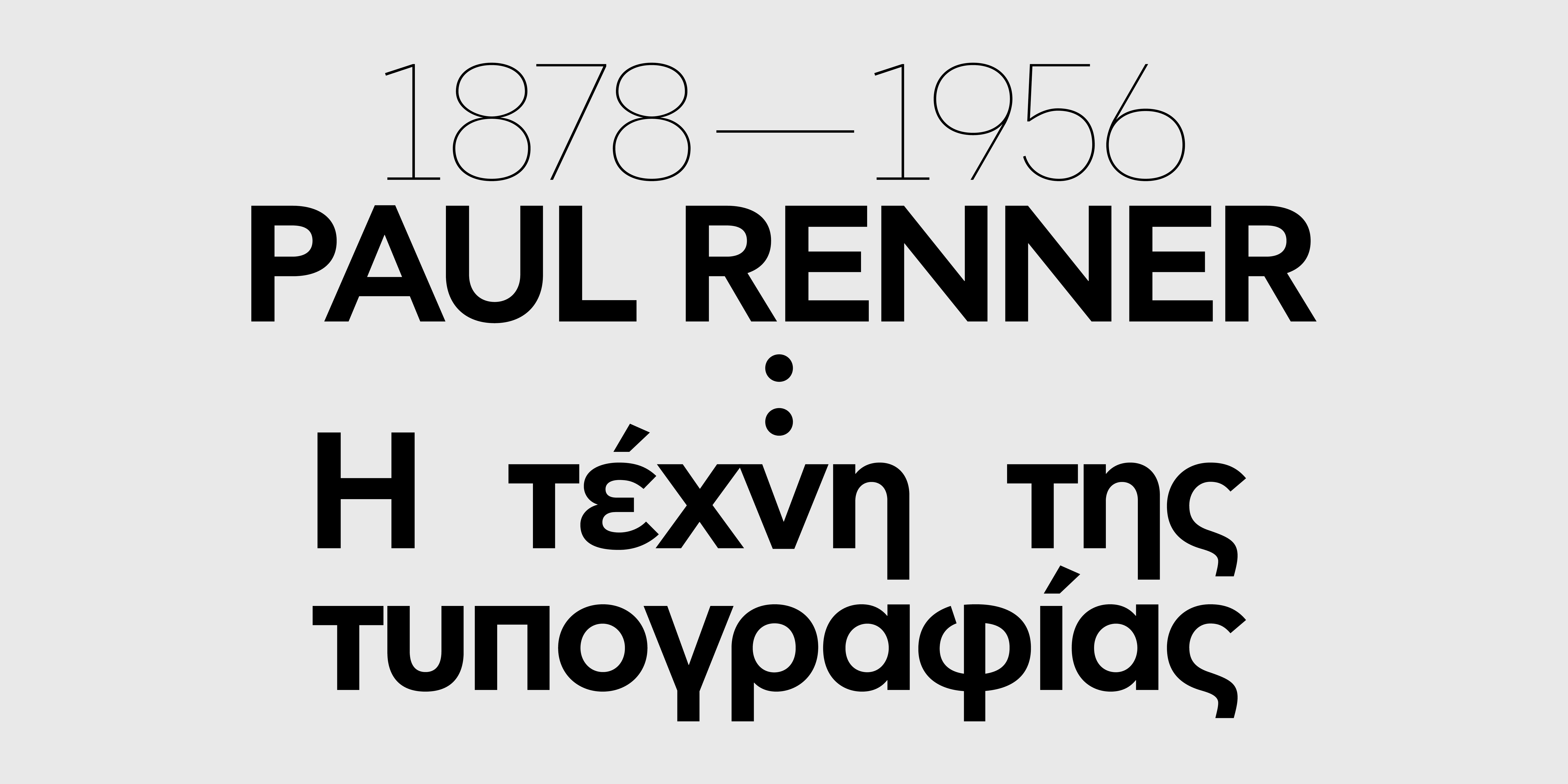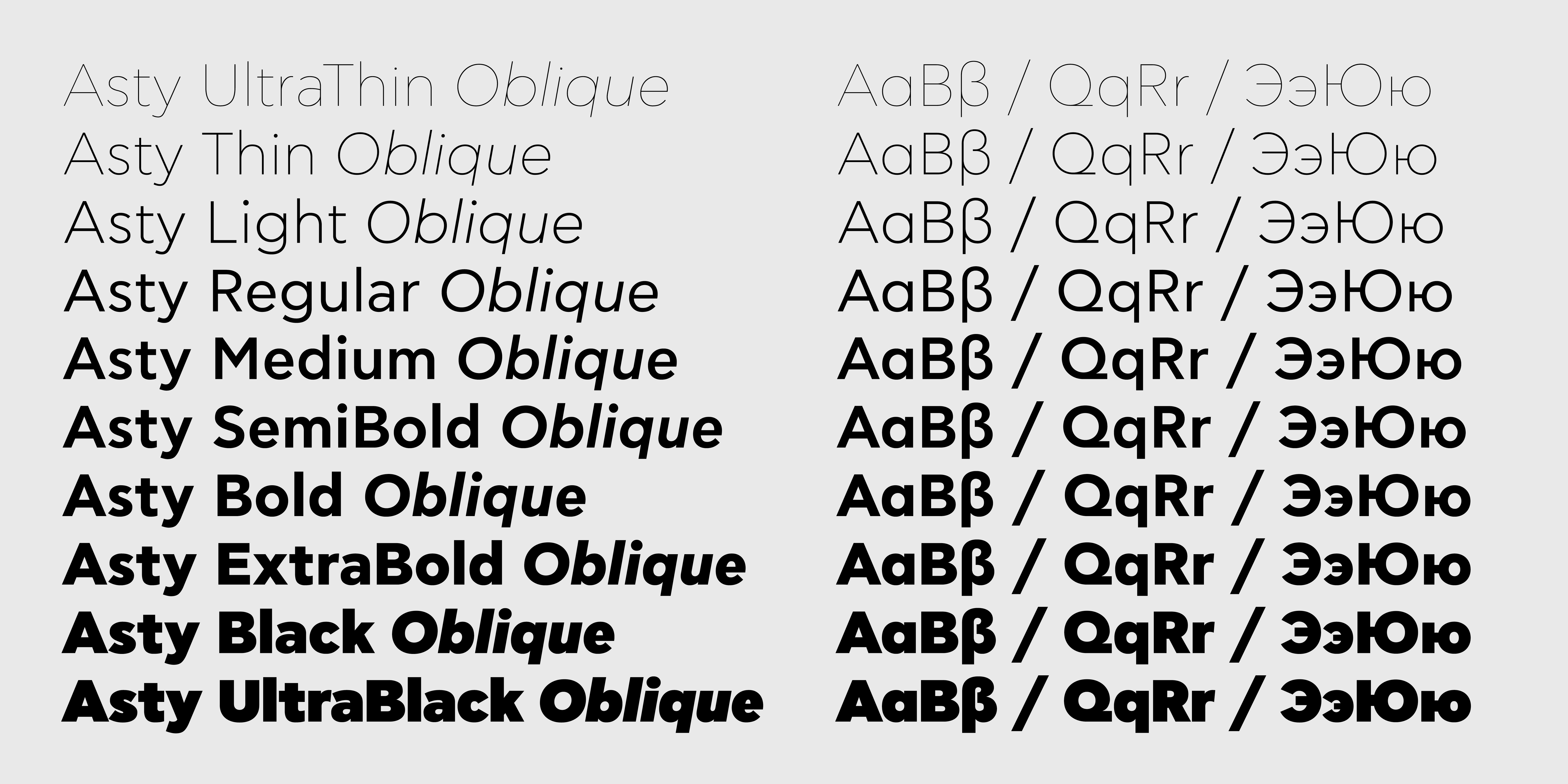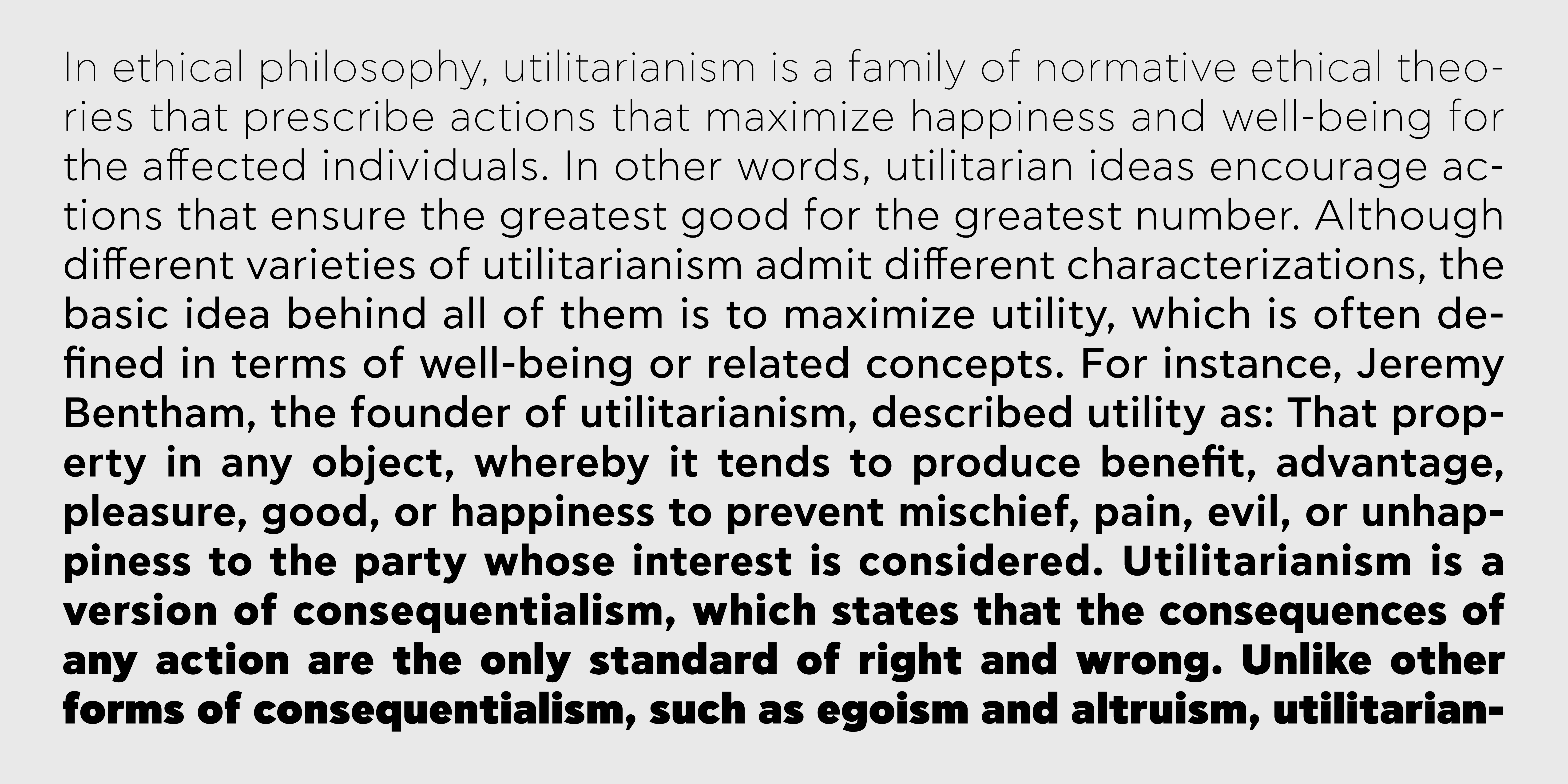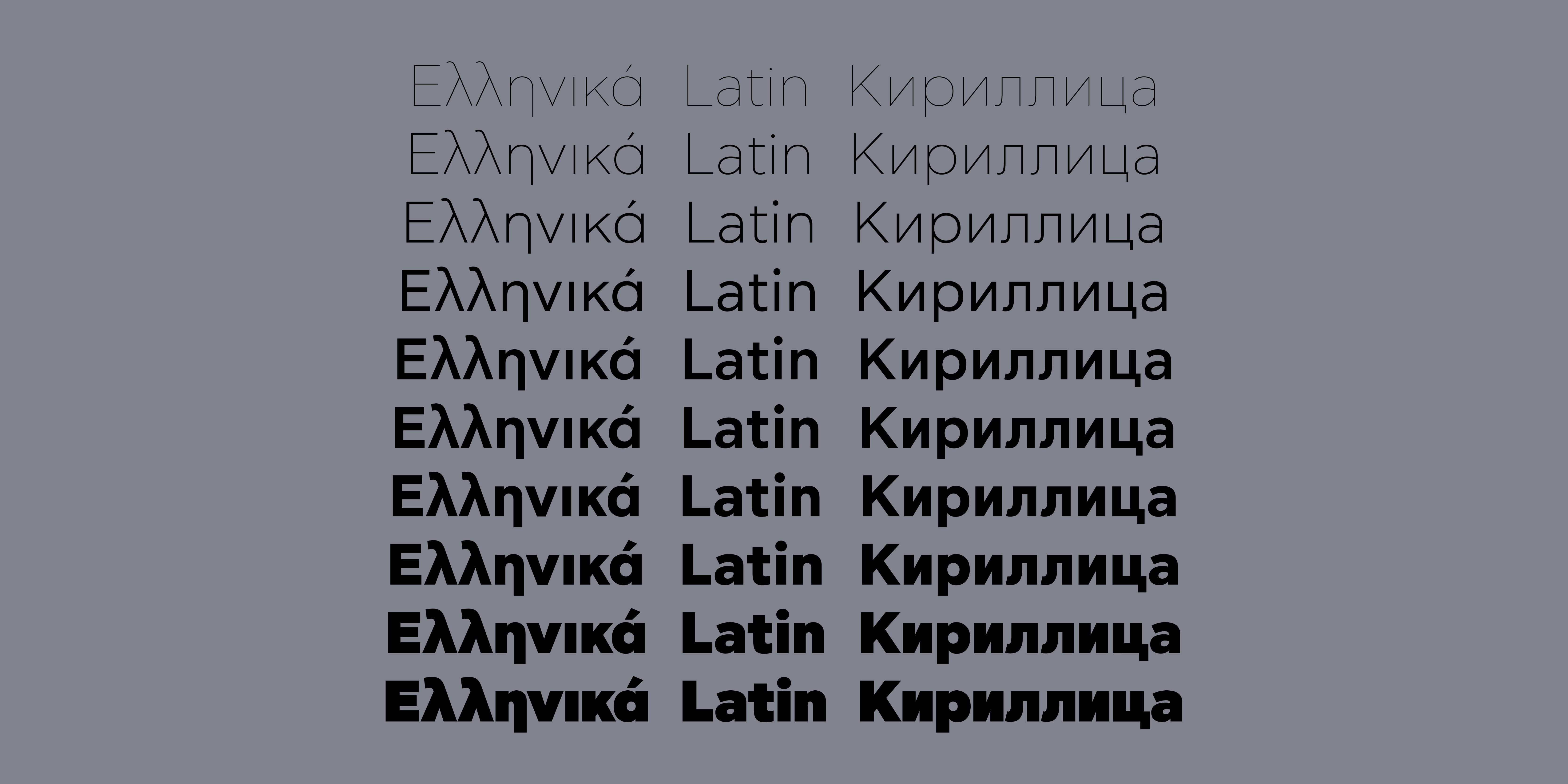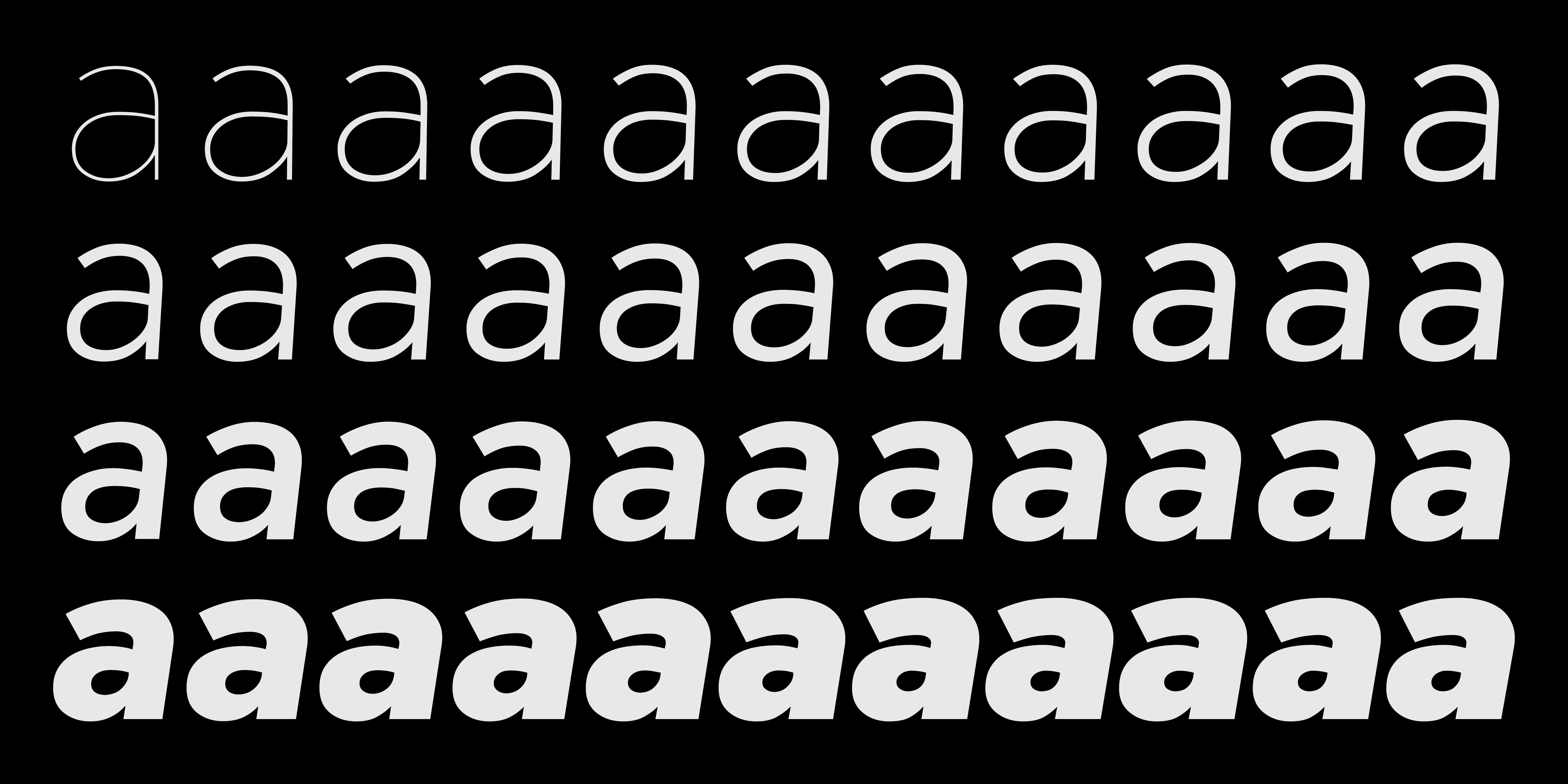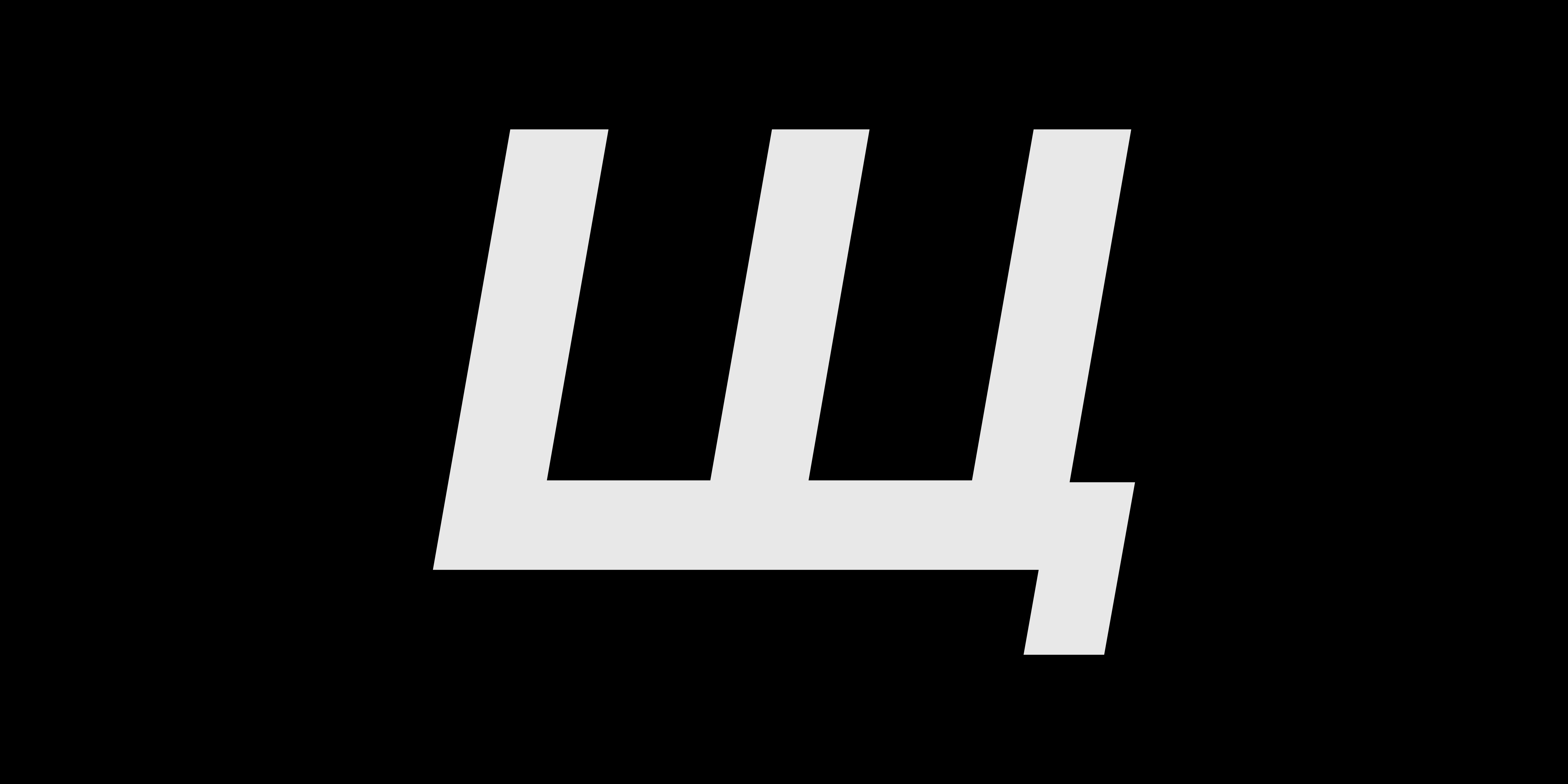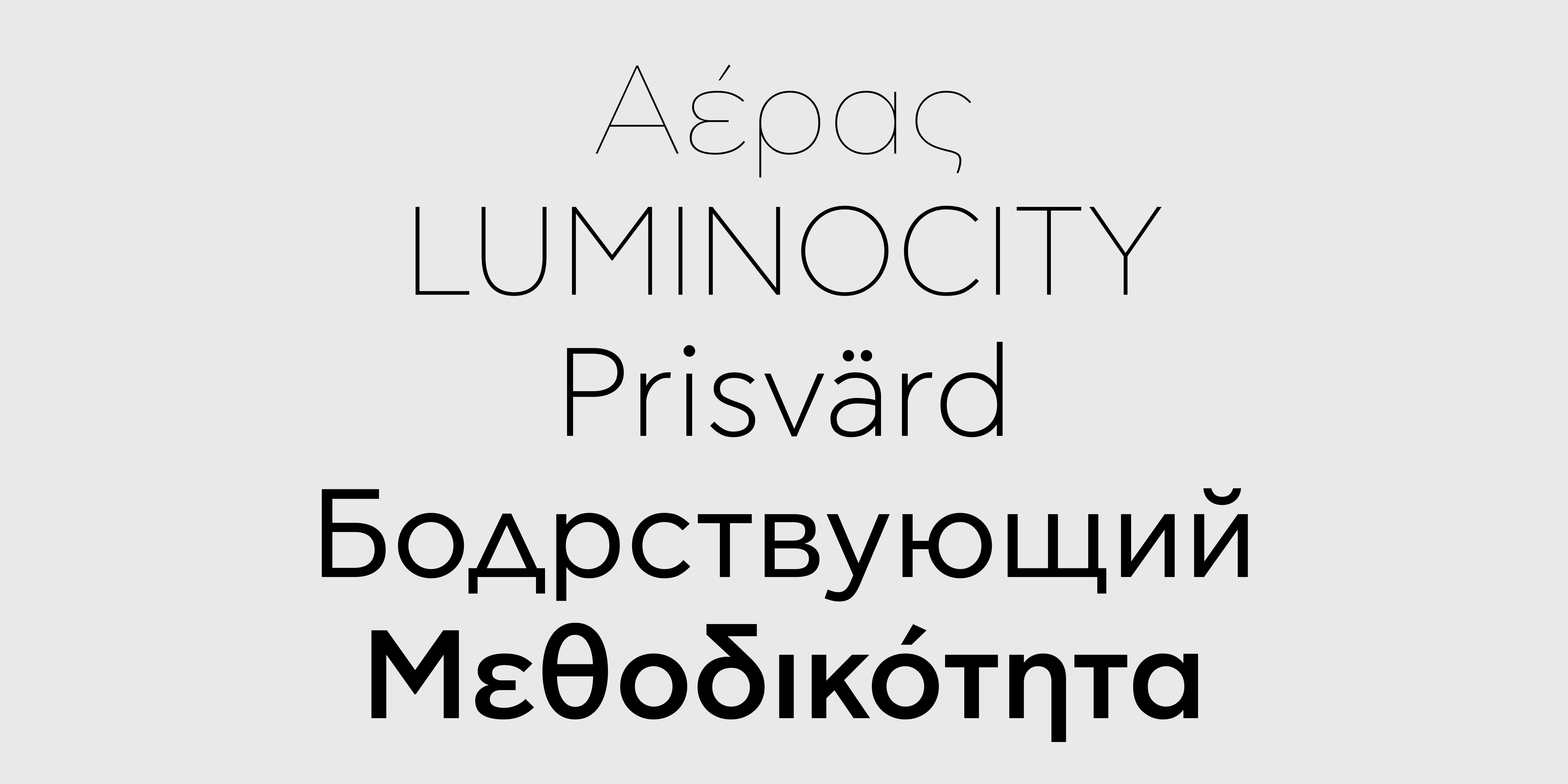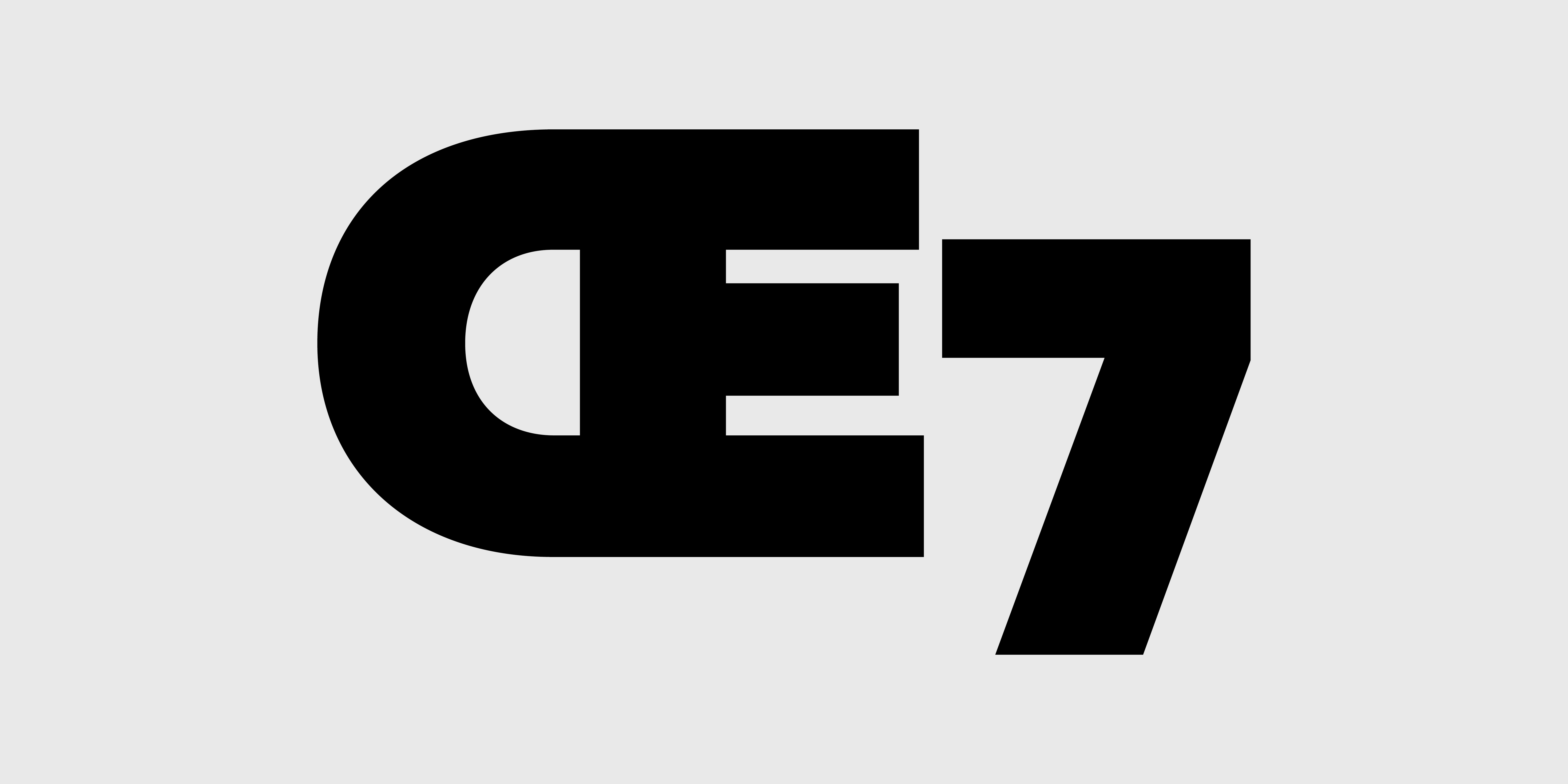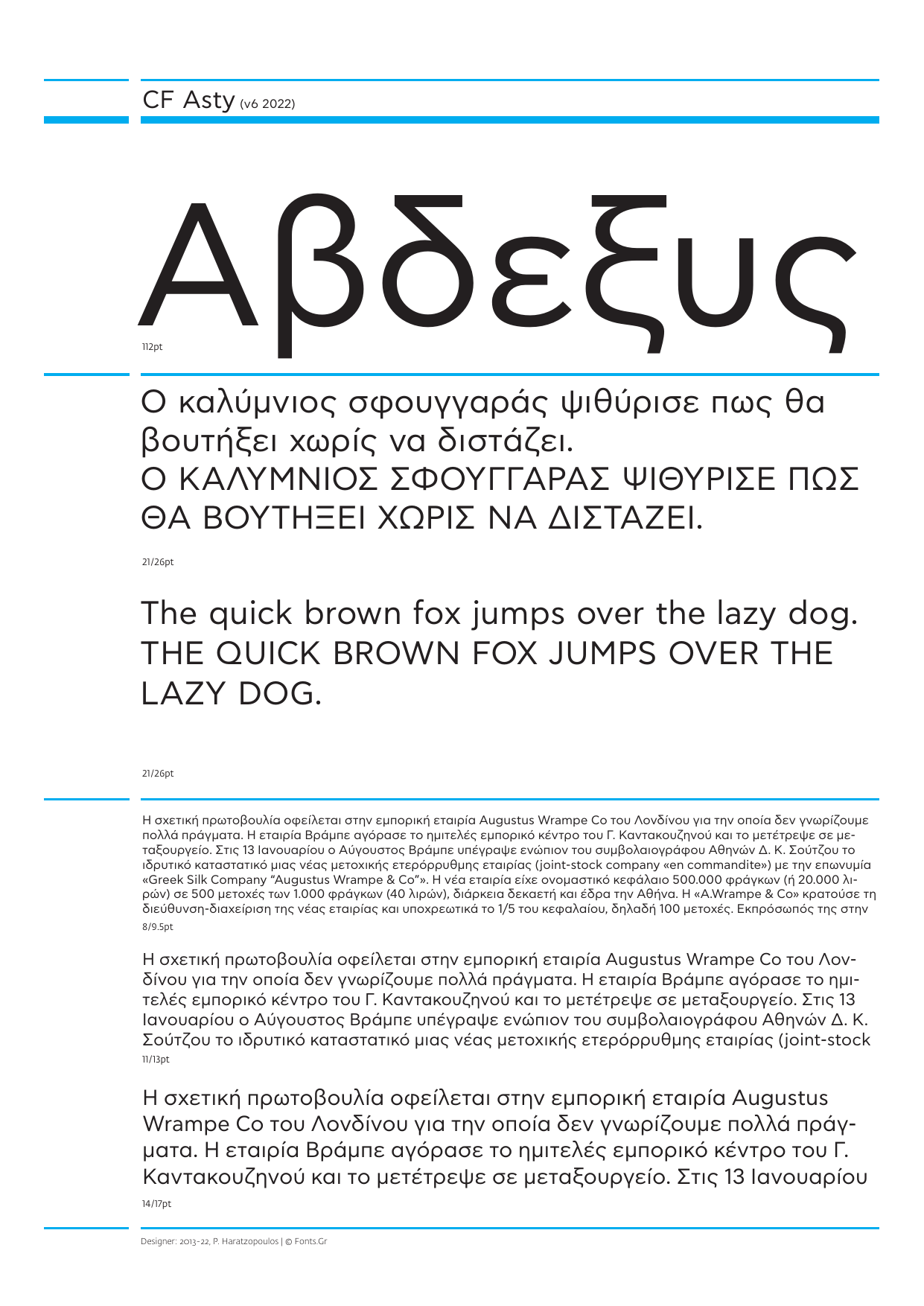
Asty
Μια ισόπαχη γεωμετρική γραμματοσειρά με αναφορές στις αρχές του 20ου αιώνα, την αστική σήμανση και τη σχεδιαστική απλότητα της Futura του Paul Renner. Η CF Asty δεν ακολουθεί πιστά όμως την αυστηρή γεωμετρία της Futura, εμπεριέχοντας ταυτόχρονα και ανθρωπιστικά στοιχεία σχεδιασμού όπως αντίστοιχες δημοφιλείς ισοπαχείς γραμματοσειρές (Avenir, Gotham, Neutraface, Gill Sans κ.α.). Αυτή η προσέγγιση, σε συνδυασμό με το αρκετά μεγάλο οφθαλμό (ύψος πεζών), την καθιστούν ευανάγνωστη τόσο σε πυκνό κείμενο όσο και σε τίτλους. Ιδιαίτερη σημασία δόθηκε στην καθαρότητα των ελληνικών χαρακτήρων, που χωρίς σχεδιαστικές υπερβολές, συνδυάζονται απόλυτα με το ύφος και την απλότητα των λατινικών. Η νεότερη έκδοση (2022) υποστηρίζει Greek, Western, Extended Latin και Cyrillic character sets καθώς και 5 είδη αρίθμησης. Είναι διαθέσιμη και σε Variable αρχείο χωρίς επιπλέον χρέωση.